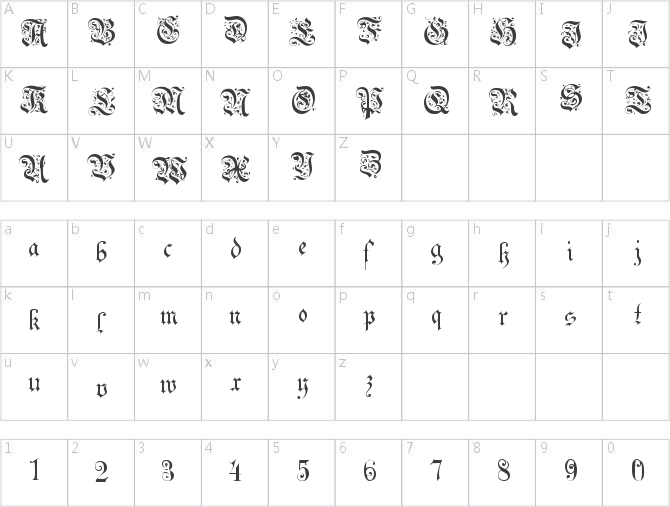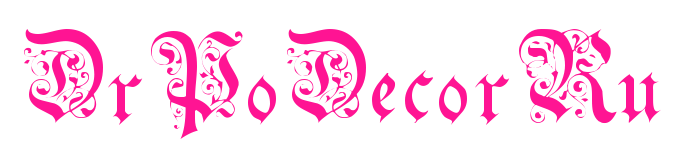
DrPoDecorRu 詳情頁(yè)
DrPoDecorRu
DrPoDecorRu字體字庫(kù)是一款讓人賞心悅目、百看不厭的英文字體,適合各類廣告和產(chǎn)品包裝設(shè)計(jì)應(yīng)用,字體大小0.22MB,格式為ttf字體,上傳用戶是隨緣゜,作者/版權(quán)方為未知